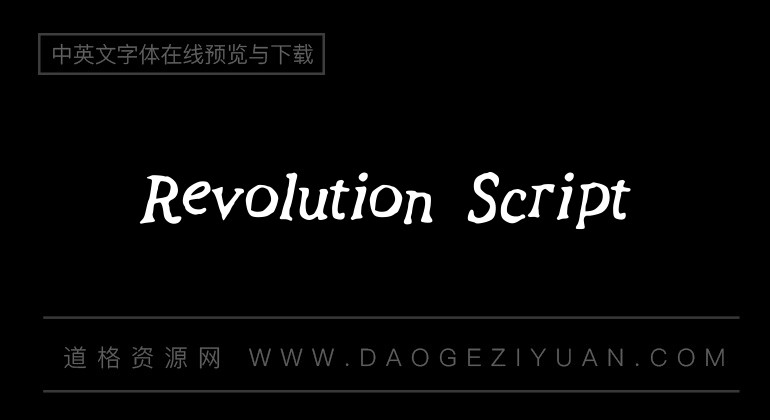
Revolution Script
Revolution Script 是一种手写风格的字体,具有浪漫和时尚的感觉。它的字母形状优美,流畅而具有艺术性,适用于各种印刷品和设计项目,如海报、包装、书籍封面等。该字体的特点是每个字母都具有手写的感觉,让文本看起来更加个性化和独特。 Revolution Script 字体包括大写字母、小写字母、数字和标点符号,支持多种语言和字符集,并提供多种字体格式,如 TrueType、OpenType 和 Webfont,可以适用于不同的应用场景和平台。
Revolution Script是一款非常不错的手写艺术字体,具有很好的视觉感,适合于文化类的宣传设计、商业类品牌的广告和产品包装设计以及个性化文字排版等较多场景。